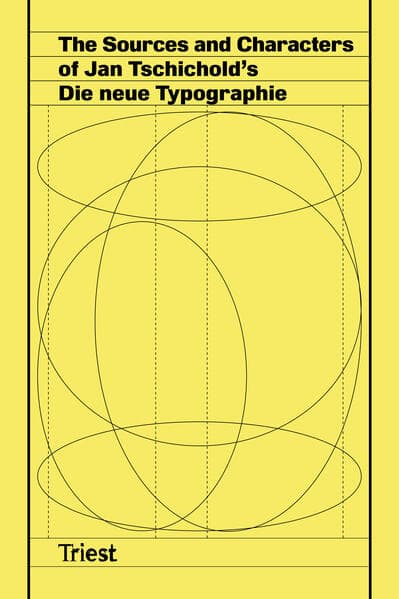
Jan Tschichold war ein bedeutender deutscher Typograf, Buchgestalter und Schriftsteller, der als einer der Pioniere des modernen Grafikdesigns gilt. Geboren 1902 in Leipzig, entwickelte er innovative typografische Prinzipien und setzte sich für klare, funktionale Gestaltung ein. Sein bekanntestes Werk, Die neue Typographie (1928), bildete die Grundlagen des modernen Designs und beeinflusste Generationen von Designern. Tschichold war ein Verfechter der Verwendung von serifenlosen Schriften und einer strukturierten Anordnung von Text und Bild. Nach seiner Emigration aus Deutschland in den 1930er-Jahren setzte er seine Arbeit in der Schweiz und später in Grossbritannien fort, wo er weiterhin die typografische Praxis prägte. In Band 1 werden sowohl die Wurzeln, Quellen als auch die Auswirkungen der Neuen Typographie beleuchtet und gezeigt, wie Tschichold auf vorhandene Quellen zurückgriff, um seine eigenen Ideen zu formulieren. Die Essays erforschen die Ursprünge ähnlicher Prinzipien im frühen 20. Jahrhundert in Deutschland, der Tschechoslowakei und Dänemark. Die Publikation zeigt dann die Auswirkungen von Tschicholds Ideen auf die Gestalterszene weltweit, indem sie die Verbreitung, Rezeption und Nachwirkungen von Die Neue Typographie untersucht. Seine Ideen verbreiteten sich unmittelbar in der Schweiz, Grossbritannien und den USA, aber auch verschiedene nationale Szenen in ganz Europa und Asien griffen die Prinzipien der Neuen Typographie auf, wo sie angenommen oder neu verhandelt wurden. Die Publikation ist als thematische multi- und transnationale Geschichte des Grafikdesigns konzipiert, die die Entwicklung von Jan Tschicholds Theorien im Laufe des 20. Jahrhunderts verfolgt. Das Buch erweitert den Rahmen von Die neue Typographie, indem es den zeitlichen Umfang ausdehnt, den geografischen Kontext erweitert und den Diskurs über die Bewegung bereichert. Band 2 widmet sich den Originalquellen von Tschicholds Bibliografie. Er verwendete dafür eine mehrschichtige Logik und organisierte die Quellen nach Typologien (Zeitschriften, Sonderausgaben, Bücher, Normen) und Sprachen. Trotz ihres offensichtlichen Einflusses auf sein Denken blieben diese Quellen aufgrund ihrer Seltenheit und den damit verbundenen Schwierigkeiten bei der Konsultation weitgehend unerforscht. Um dieser Situation entgegenzuwirken, rekonstruiert die vorliegende Publikation den Bestand bibliografischer Quellen, auf die Tschichold zurückgriff, und bietet ein besseres Verständnis des grösseren kulturellen Kontexts von Die neue Typographie. Die Forscherinnen und Forscher identifizierten alle 120 Quellen und sammelten sie, wo möglich, in Original- oder Faksimile-Ausgaben. Band 2 kombiniert diese Forschung mit einer visuellen und textlichen Dokumentation der Referenzen, deren Inhalte in hochwertigen Fotografien mit Beschreibungen, sachlichen Informationen und weiteren Lesemöglichkeiten ergänzt werden. Mit Beiträgen von Jonas Berthod, Matthieu Cortat-Roller, Gilles Gavillet, Vincent Levrat, Nicolas Polli, François Rappo, Martin Søberg, Davide Tomatis